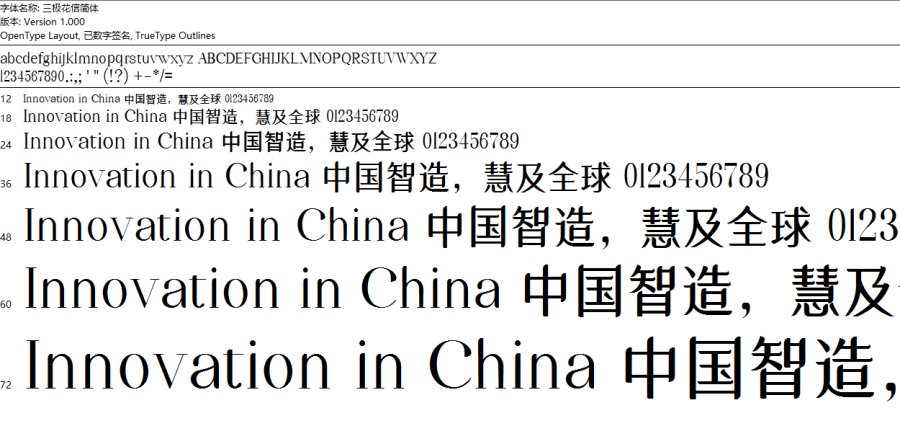
字体名称:
三极花信简体
字体介绍:
三极花信简体是三极字库推出的一款具有典雅气质的风格化黑体作品。兼具了黑体的简洁和宋体的雅致特征。整体字形方正,刚柔相济,优雅大方。其横竖笔画横纵,横竖笔画粗细反差较大,加以弯钩柔美曲线点缀,突显典雅之风格。
适用范围:
适用用于商业广告、书刊出版、产品包装及界面设计标题,店招牌匾。
字形预览展示: